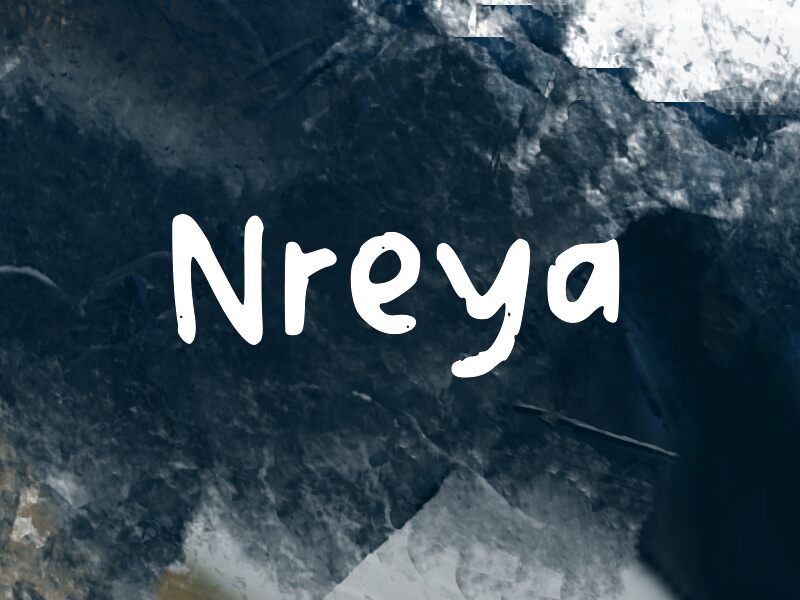
Nreya par Wep est une police brush gratuite qui capture l'esprit décontracté du lettrage peint à la main. Les lettres ont un aspect vif et personnel, avec des traits épais et arrondis, une légère irrégularité et un rythme dynamique qui évite tout côté trop soigné ou rigide.
Elle est idéale pour les titres d'affiches, l'identité visuelle de cafés, le packaging, les graphiques pour les réseaux sociaux et les textes courts où la touche humaine compte plus que la précision. En tant que police gratuite, Nreya fonctionne également très bien pour les titres ou les grandes citations, car ses formes de pinceau larges et son espacement aéré conservent cette énergie brute de marqueur, même sur quelques mots.
Nreya
Présentation et spécimen de la police Nreya
Table des caractères de la police Nreya
Table des caractères de Nreya : Latin de base, page 1
Glyphes de la police Nreya — Latin de base, page 1